Conversor de fontes estranhas do nome Discord | Letras com símbolos para apelido | Copiar e colar
O Discord é uma das melhores plataformas para bate-papo no mundo dos jogadores, embora possa ser usado para outros fins. No entanto, você deve sempre procurar maneiras de se destacar da multidão ao transmitir uma mensagem, e uma delas é com as letras do Discord.
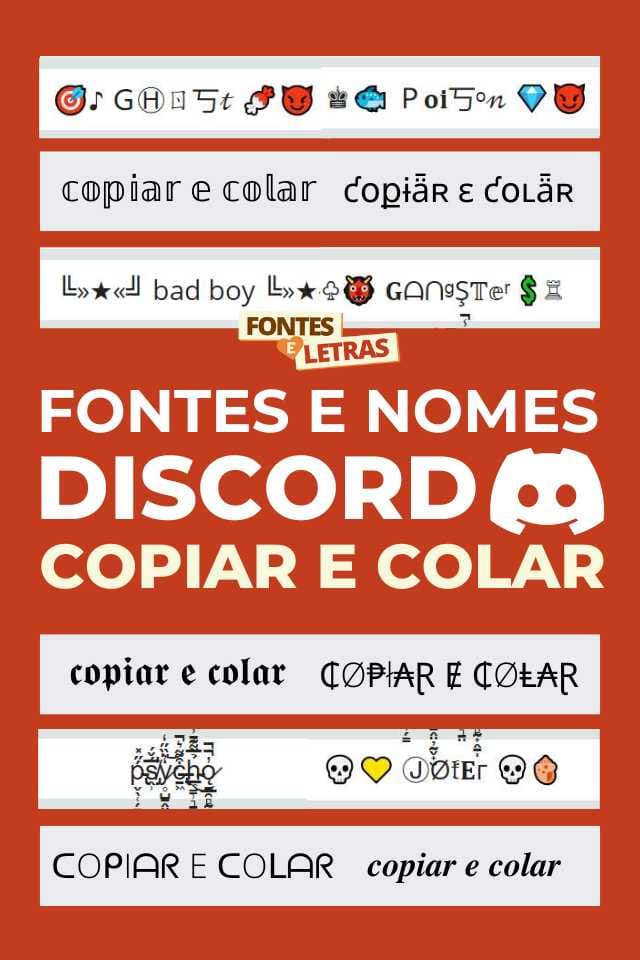
As diferentes fontes e tipografias do Discord ajudam a garantir que a mensagem importante que você precisa transmitir não se perca na multidão e que você atinja seu objetivo.
1. Importância das cartas personalizadas para o Discord
Há muitos motivos pelos quais as letras raras para o Discord podem ser úteis em conversas ou no servidor. Entre os mais proeminentes estão os seguintes:
# Adicionando atratividade aos servidores
Usar fontes diferentes para o Discord nos servidores pode ajudá-lo a enfatizar determinados pontos em suas mensagens, além de ajudá-lo a se expressar de maneira fácil e dar um toque exclusivo às suas comunicações ou mensagens.
# Crie um nome de usuário original
Usar fontes diferentes para o Discord é fundamental para que seu nome de usuário se destaque da multidão e tenha a aparência que você deseja impressionar e comunicar aos outros usuários.
Há muitas opções, portanto, temos certeza de que você encontrará a opção certa.
# Criação de mensagens com um toque extra
As letras raras do Discord também permitem que você dê um toque extra às suas mensagens ou as formate como desejar, de acordo com as fontes do Discord que estão disponíveis em plataformas externas.
Você pode usar essas fontes do Discord em seus status, acrescentando um estilo único e estético ao seu perfil e conteúdo.
2. Alterar letras Apelido do Discord
Em primeiro lugar, você terá que ir para a parte superior desta página e, na caixa de texto, colocar o usuário e, em seguida, copiar a fonte do Discord que você mais gosta. Depois disso…
3. Mensagens com letras estranhas para o Discord
As fontes do Discord podem ser perfeitamente complementadas com um toque de emoticons no início ou no final do texto. Para isso, existem sites, como o Cute Kaomoji, que oferecem muitas opções de emoticons.
Você pode ser tão criativo quanto quiser, intercalando emojis entre as fontes do Discord para dar um efeito especial e se comunicar de uma forma mais criativa e atraente com as fontes do Discord.
4. Uso de diferentes formatos de fontes para o Discord
Vamos começar com o básico, ou seja, formatos de fonte raros para o Discord, e depois você pode explorar isso e combiná-lo com opções de fonte muito mais avançadas.
# Texto em itálico
Se você quiser que o texto fique inclinado ou em itálico, basta adicionar um asterisco (*) no início e no final da mensagem. A formatação será exibida até que você pressione "entender" e envie a mensagem.
# Texto em negrito
Para aplicar a formatação em negrito no Discord, você deve adicionar dois asteriscos (**) no início e no final da mensagem e enviá-la. Você terá criado um formato nas fontes do Discord.
# Texto sublinhado
Se você quiser sublinhar uma mensagem inteira ou parte de uma mensagem no Discord, basta adicionar dois sublinhados (__) no início e no final do texto que deseja formatar.
# Texto riscado
Por fim, se você quiser riscar algumas fontes do Discord para enfatizar uma parte da mensagem, deverá colocar dois tildes (~~) nas duas extremidades do texto que deseja modificar.
5. Geradores de texto, a melhor opção de fonte para Discord
Para ir além do básico e poder usar letras estranhas e mais originais no Discord, a melhor opção é usar geradores de texto ou fontes para o Discord, que são muito fáceis e rápidos de usar.
Atualmente, existem diferentes geradores ou conversores de letras que podem ajudá-lo a realizar essa tarefa sem ter que se preocupar com a busca.
A grande vantagem é que eles oferecem um grande número de opções para letras personalizadas do Discord, e tudo o que você precisa fazer é digitar a mensagem, aguardar os resultados serem gerados, copiar o texto e colá-lo no Discord.
Você não só obterá fontes bonitas ou estranhas, mas também símbolos que darão um toque extra à sua mensagem. Basta acessar o gerador, seguir as etapas que mencionamos e pronto!